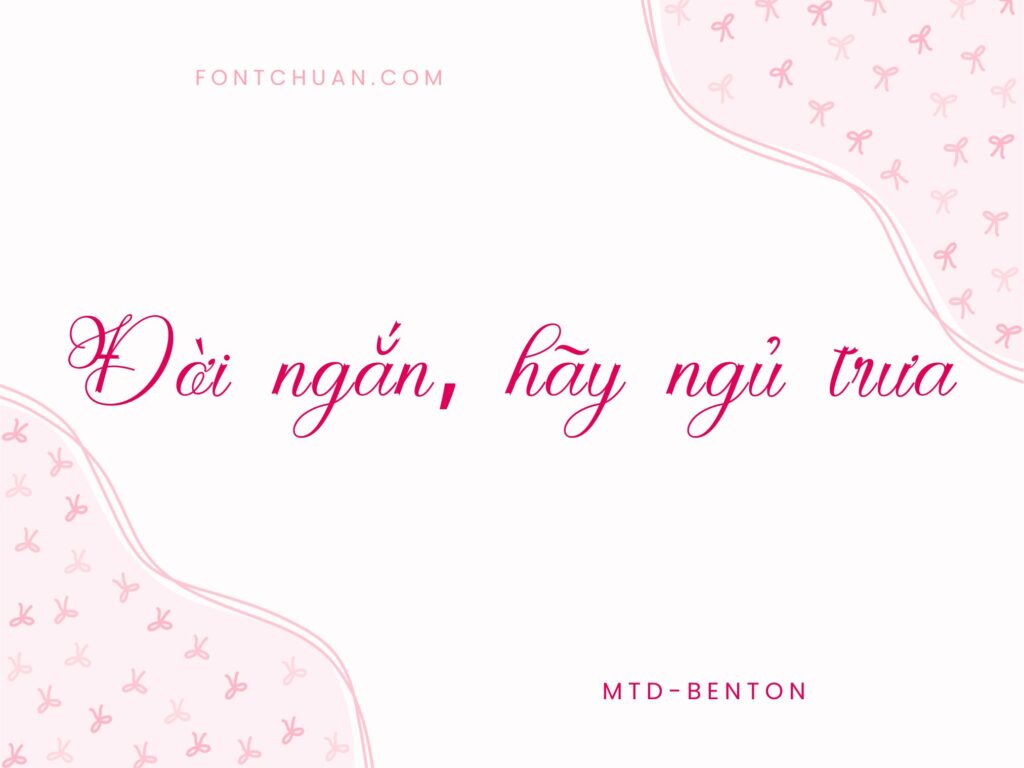
Font MTD Benton Việt Hóa
Benton là một font chữ ấn tượng được thiết kế bởi Madjack Studio, mang phong cách hiện đại với các đường nét tinh tế và chuyên nghiệp. Font này sở hữu thiết kế mạnh mẽ nhưng vẫn mềm mại, phù hợp cho nhiều loại dự án thiết kế khác nhau. Để hỗ trợ cộng đồng thiết kế Việt Nam, Mộc Hạ đã Việt hóa Benton, giúp font này tương thích hoàn toàn với tiếng Việt cùng hơn 200 ngôn ngữ khác. Phiên bản Benton Việt hóa đã được thành viên Font Chuẩn sưu tầm và đăng tải nhằm giúp các nhà thiết kế có thêm lựa chọn phong phú cho các dự án sáng tạo.
Về đặc điểm thiết kế, Benton sở hữu các ký tự sắc nét, kết hợp với độ tương phản nhẹ để tạo cảm giác hiện đại và chuyên nghiệp. Font này phù hợp cho các thiết kế thương hiệu, logo, tiêu đề lớn, banner quảng cáo và các dự án thiết kế sáng tạo. Ngoài ra, Benton còn thích hợp cho các ngành nghề như quảng cáo, công nghệ và giáo dục, mang đến phong cách sang trọng và đẳng cấp. Font này cũng đặc biệt phù hợp cho các sự kiện như Valentine, Sinh nhật và các dịp lễ hội.